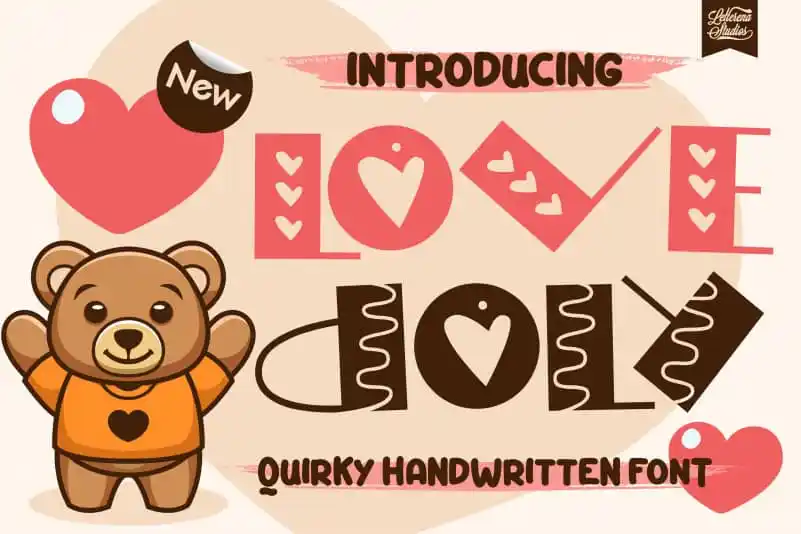
Love Doly Display Font – Download Grátis
A fonte Love Doly Display Font é perfeita para quem busca algo único e deslumbrante no design visual. Esta fonte criativa é perfeitamente adaptada para criar uma identidade visual única, tornando qualquer conceito de criação uma verdadeira estrela. Suas formas irregulares e sua originalidade singular garantirão que seu trabalho brilhe em meio a um leque diverso de opções existentes. Com Love Doly Display Font, você pode transformar seus projetos digitais num verdadeiro destaque, oferecendo aos usuários uma experiência visual inovadora e deslumbrante. Escolha esta fonte para adicionar personalidade e criatividade a seu projeto, ajudando-o a destacar-se das demais opções disponíveis no mercado.